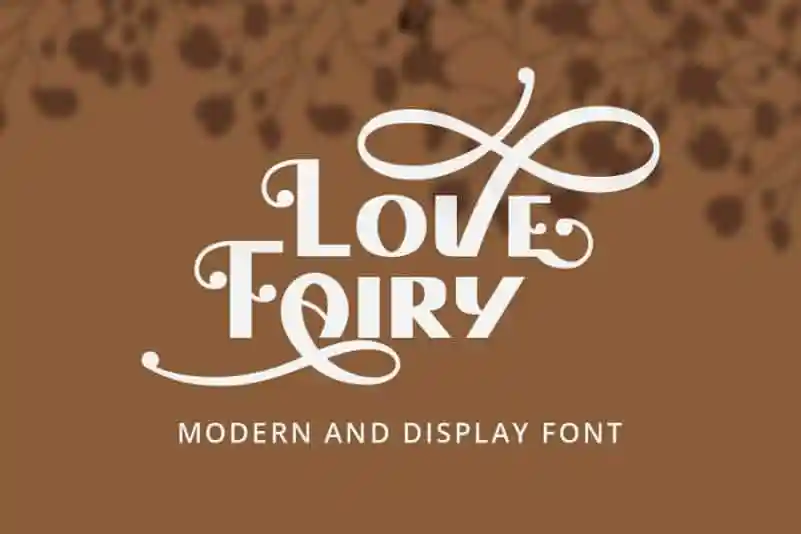
Love Fairy Display Font – Fonte Grátis
Love Fairy Display Font
Love Fairy Display Font é uma elegante sans-serif com um toque leve de alegria que faz vibrar os olhos com suas curvas fluidas. Este moderno tipo exuberante se destaca perfeitamente para assinaturas, convites de casamento, redes sociais, cartões de papelaria, logotipos, citações de tipografia, capas de revistas ou livros e cabeçalhos de sites. Além disso, a fonte é ótima para camisetas, marcação e embalagens, ajudando a criar um visual único em uma variedade de projetos visuais. Ideal tanto para designer profissional quanto para quem deseja aplicar a fonte em pequenos detalhes em suas criações pessoais, Love Fairy Display Font é uma escolha inteligente para qualquer projeto que necessite de uma combinação única e sofisticada.